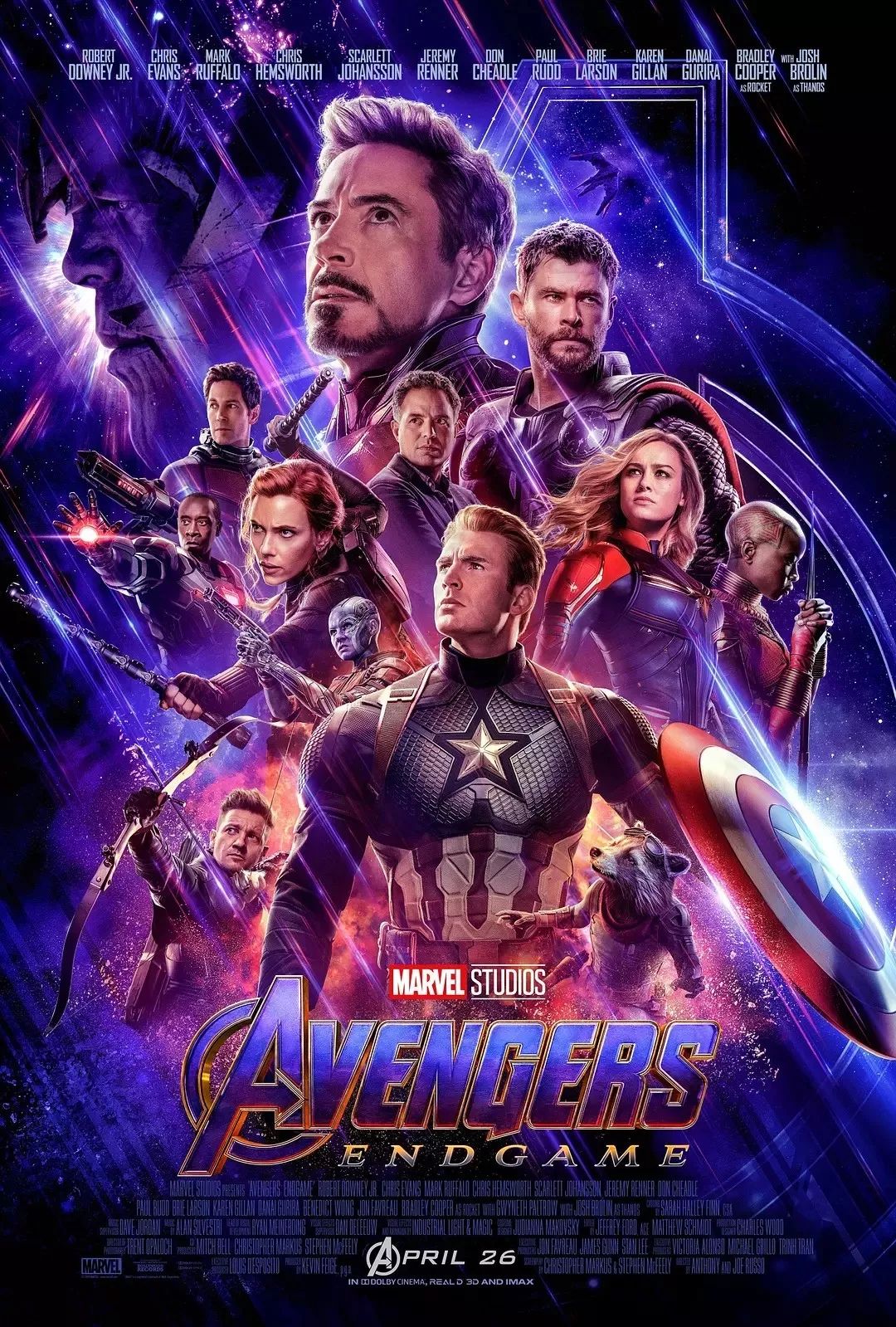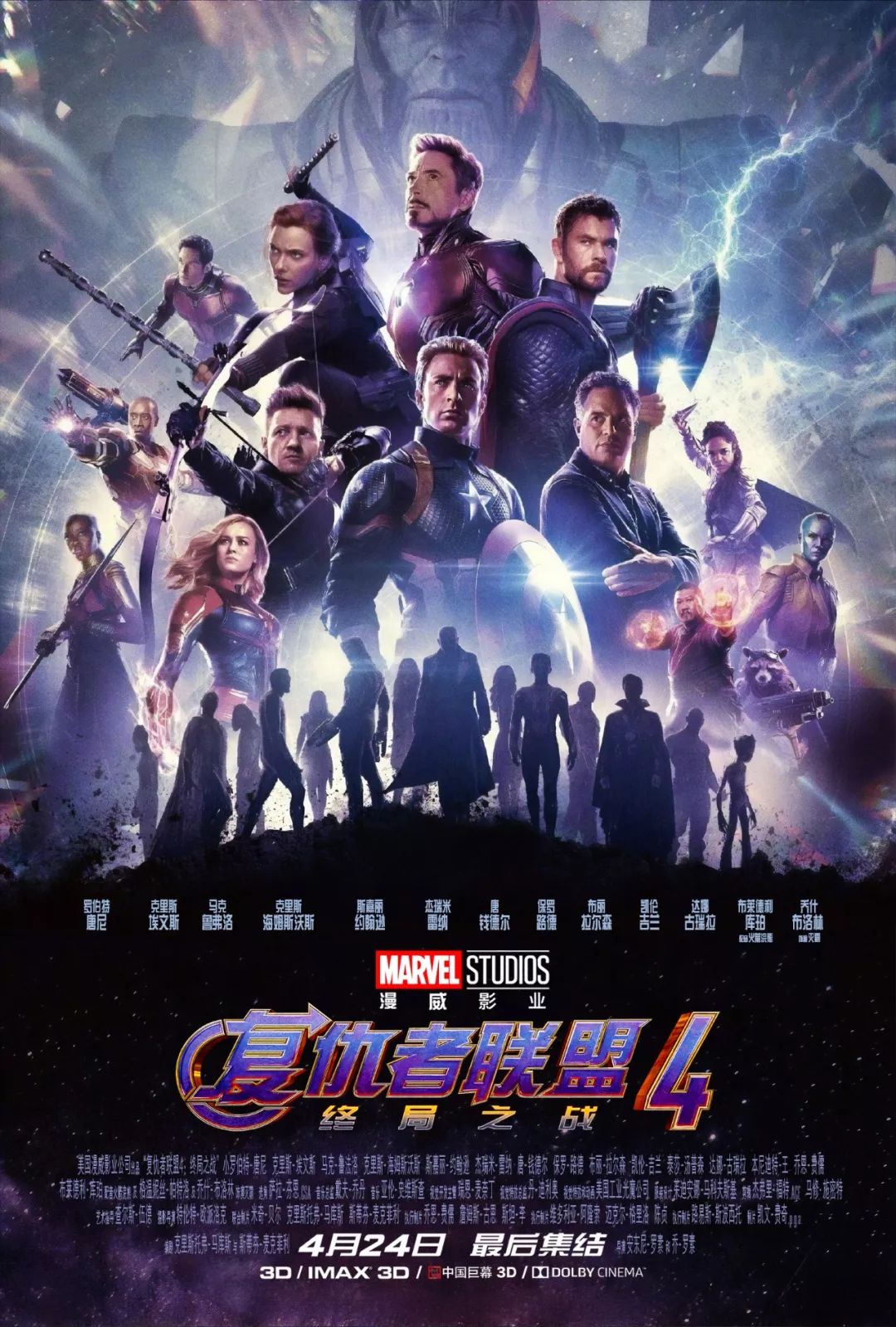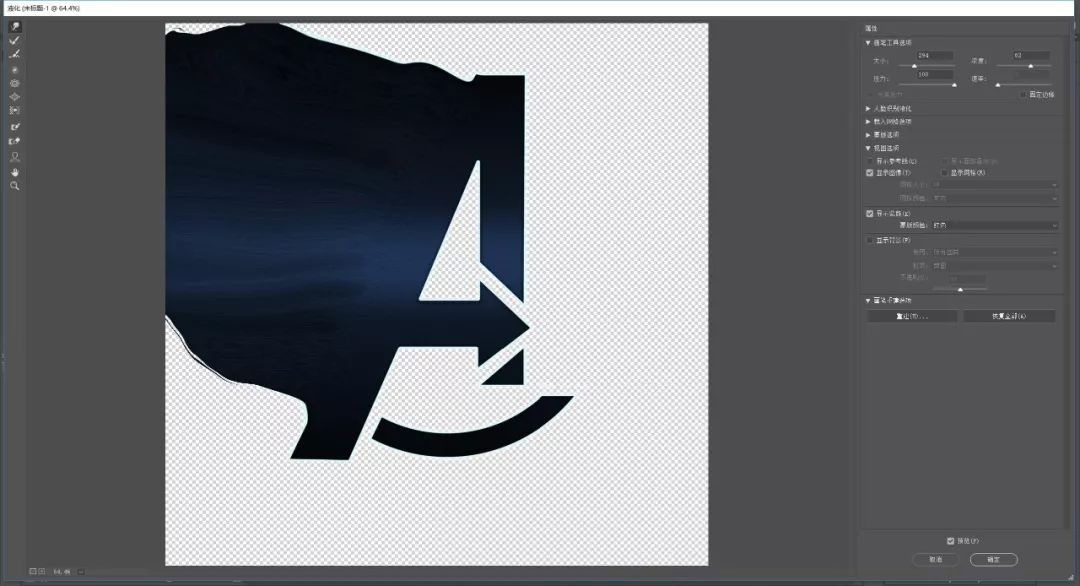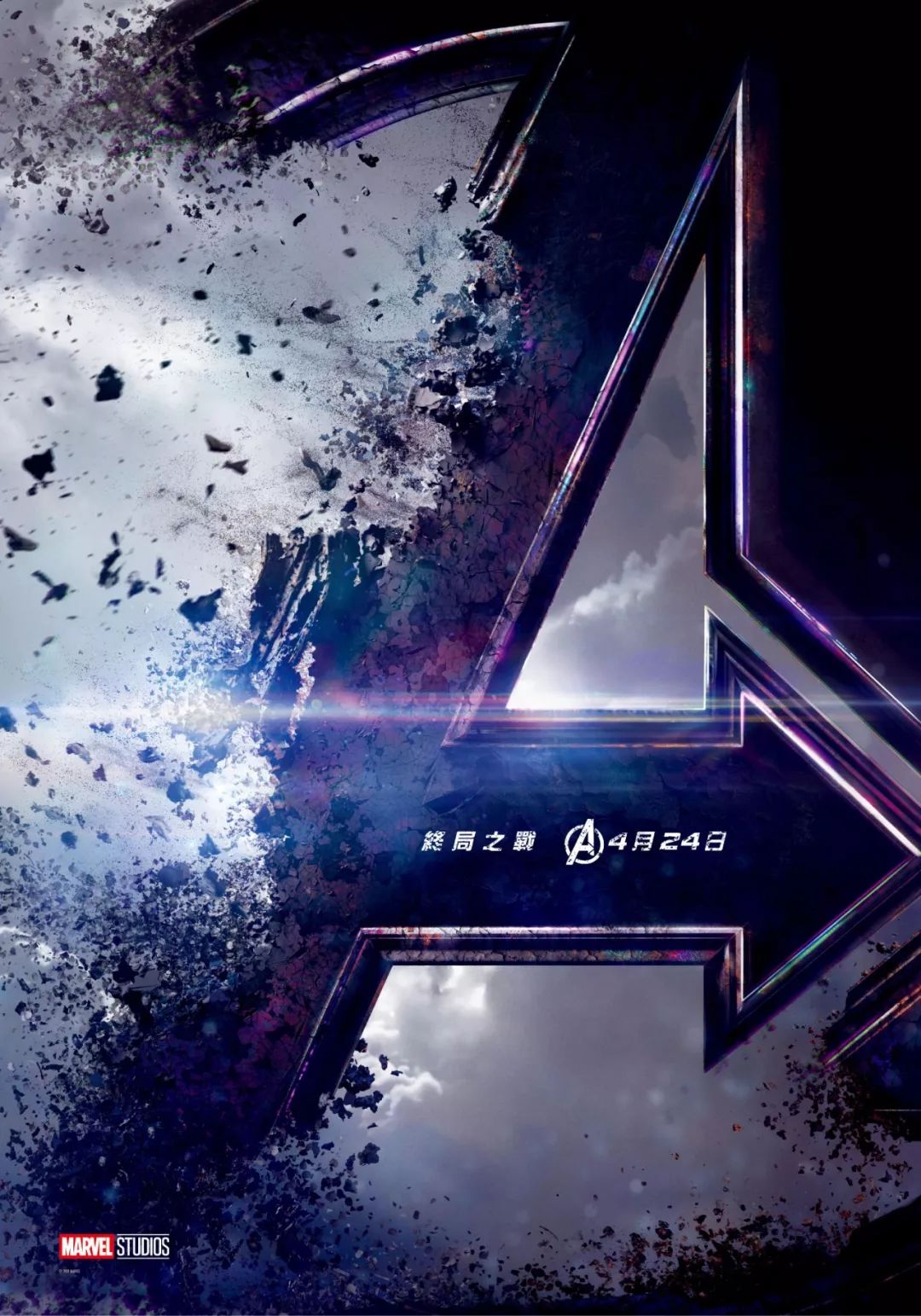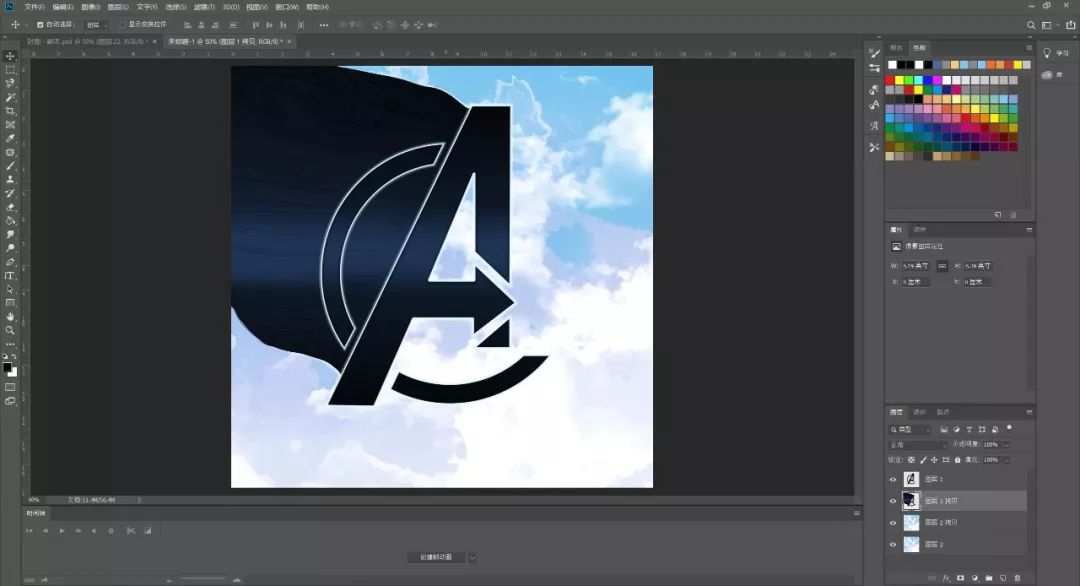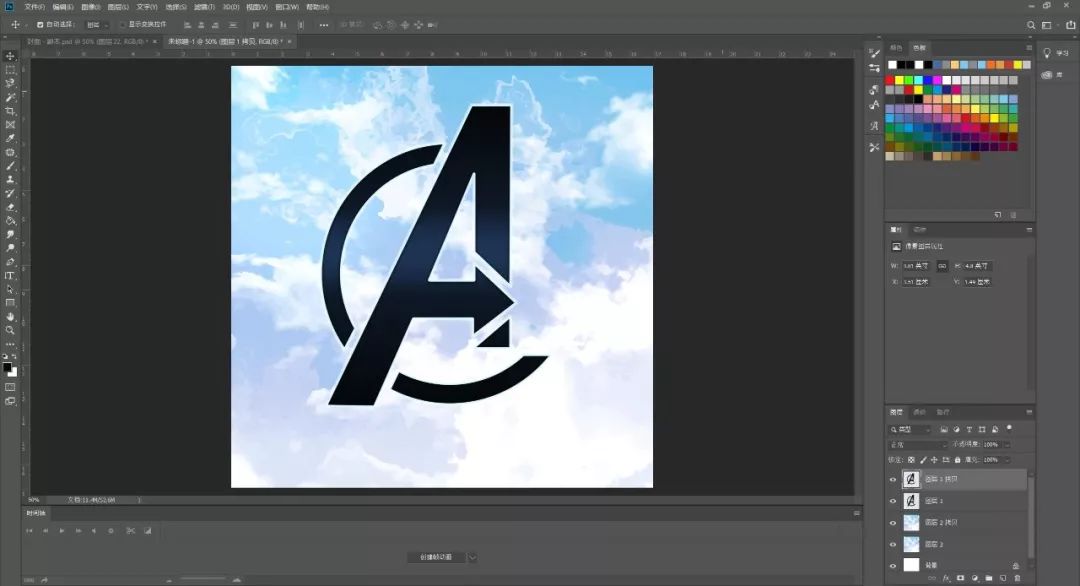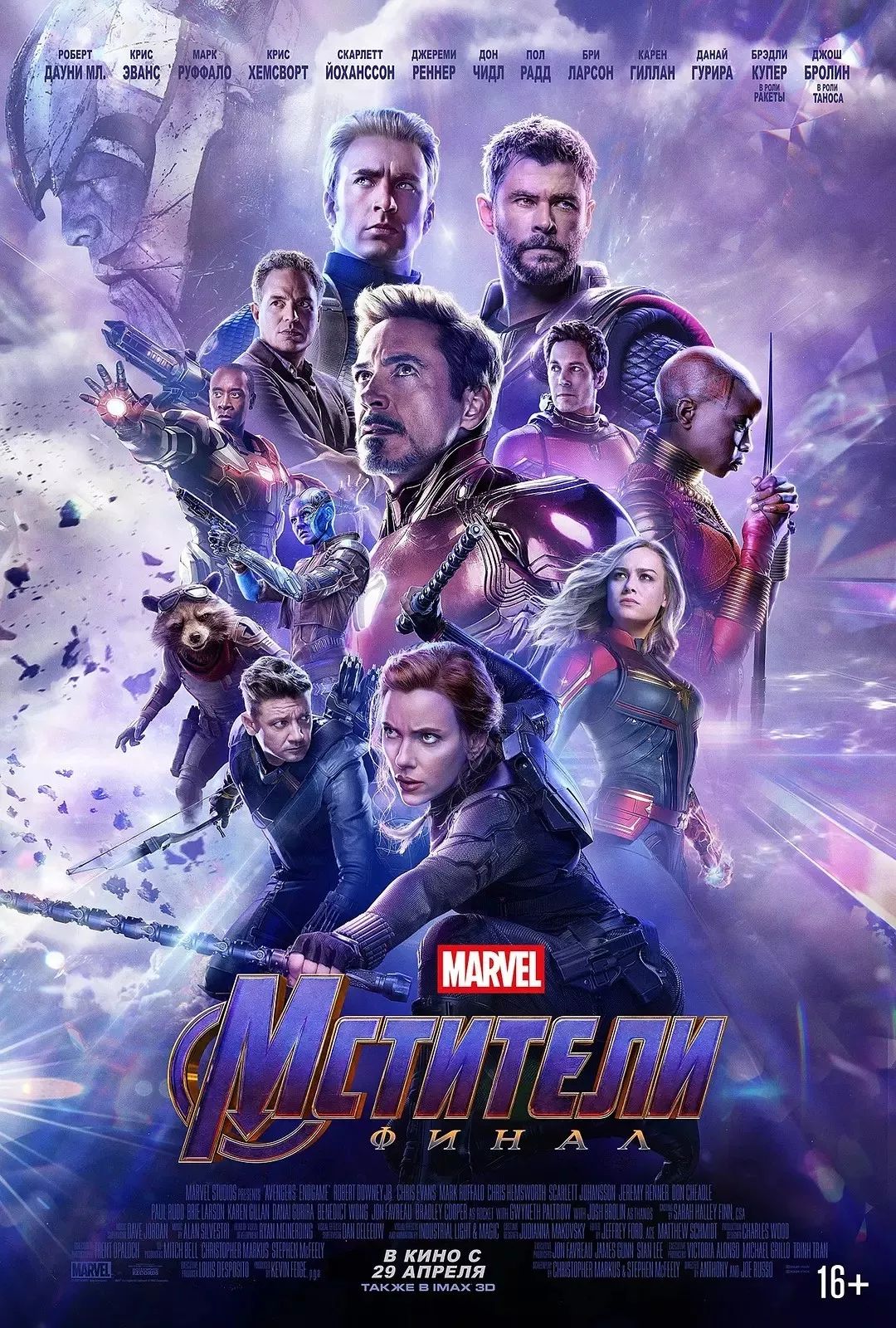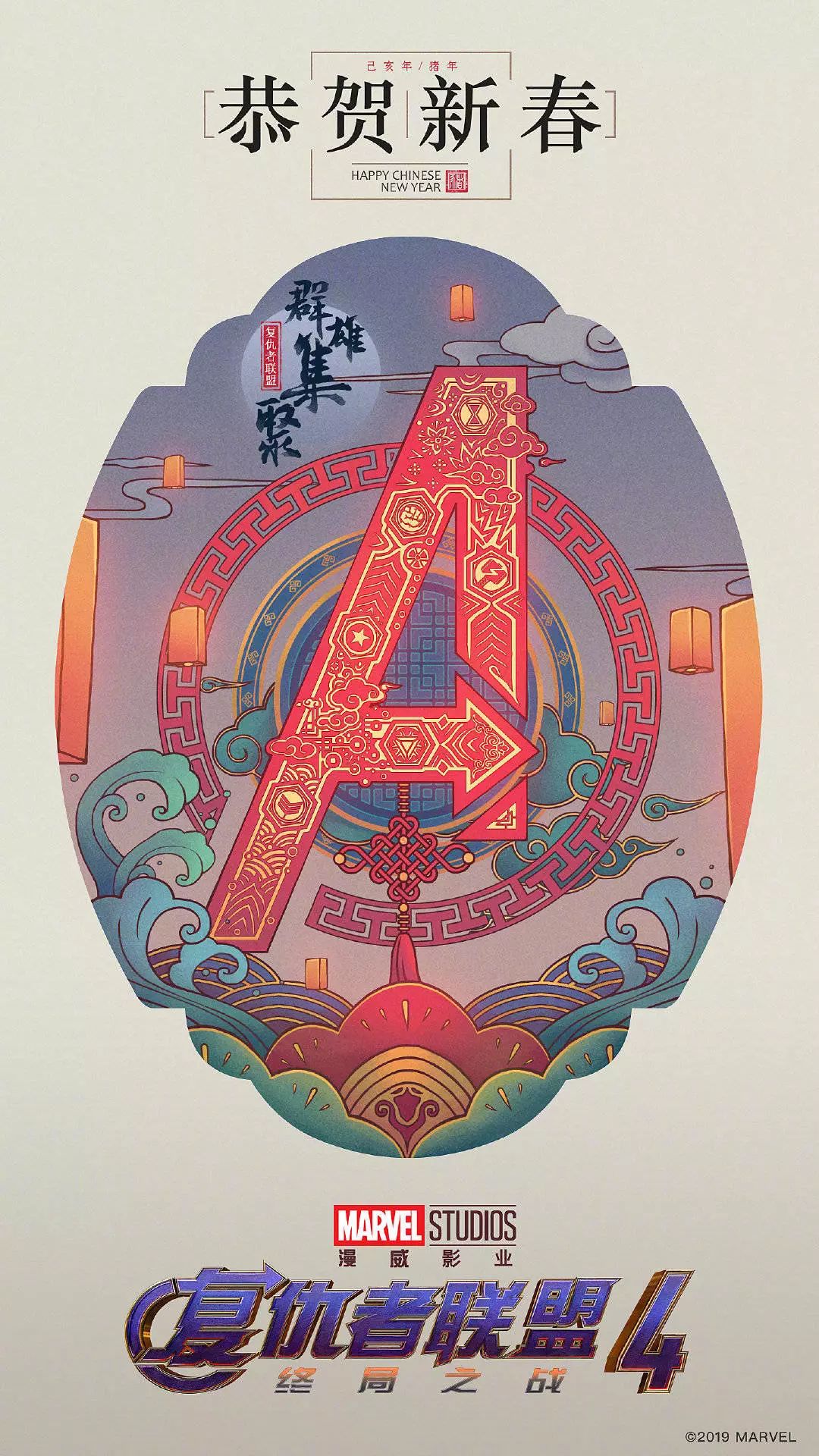
这一次,《复联4》把大陆观众宠成了亲生粉
听说4月24日,《复仇者联盟4:终局之战》就要上映了,不算时差的话,比美国的4月26日还早了2天,这在柚子看来,简直是unbelievable!
不过这还不算啥,连大陆版海报都是特供的,来一张全家福~
乍一看,三角形构图,人多势众,但对比美版,会发现很多隐藏信息~
譬如中版的上方有电影《雷神3》的武神与幸存者团队出现,而黑豹妹妹Shuri则与“化灰”团队出现在海报下方,而美版是没有的,角色精简了很多。
有意思的是俄罗斯版,不仅寡姐站c位,整体还像是中美混合的感觉(心水这款)。
不过这个粒子化特效,倒是跟预告版有所呼应,发现了吗?
我找了个漫威logo,来试试,只截取A,加一个背景图。
复制一层A,并进入滤镜>液化,不要怕难看。
把这一层移到下方,像彩旗飘飘~
给复制的A添加一个黑色的蒙版,原来的A加白色蒙版(ctrl+i可以切换),然后选择一个喷溅画笔,开始涂抹(前景色要和蒙版颜色相反哦)。
大概就这样吧,细节还要调~
那我们继续say,除了前面三版,其它国家你就不要想了,都是美版的连连看,还不如角色海报来得带劲~
还有杜比海报也不错。
过年时候发的未定档海报~
不过这都没有网友海报来得精彩,一个响指,无限续杯,宇宙无敌灭爪杯,你值得拥有~
少了灭霸,自己P一个~
其实这都是漫威粉的青春记忆,毕竟从2008到2019,已经11年了,有人追着漫威从少女变成了已婚,有人期待2019年能有人一起刷漫威。但大多数人嘛,可能还是一个人去看《复联4》。
无所谓啊,只要绿巨人摔洛基,钢铁侠抗核弹,复联的A字标……一切的一切都都留在记忆中。
回到开头,想制作一款漫威电影的海报,先要把所有关键主演都堆上去,然后找一个气势恢宏的背景图,天上要有些东西在飞,可以是飞船、尘土、人等,最后加上炫光,定稿。